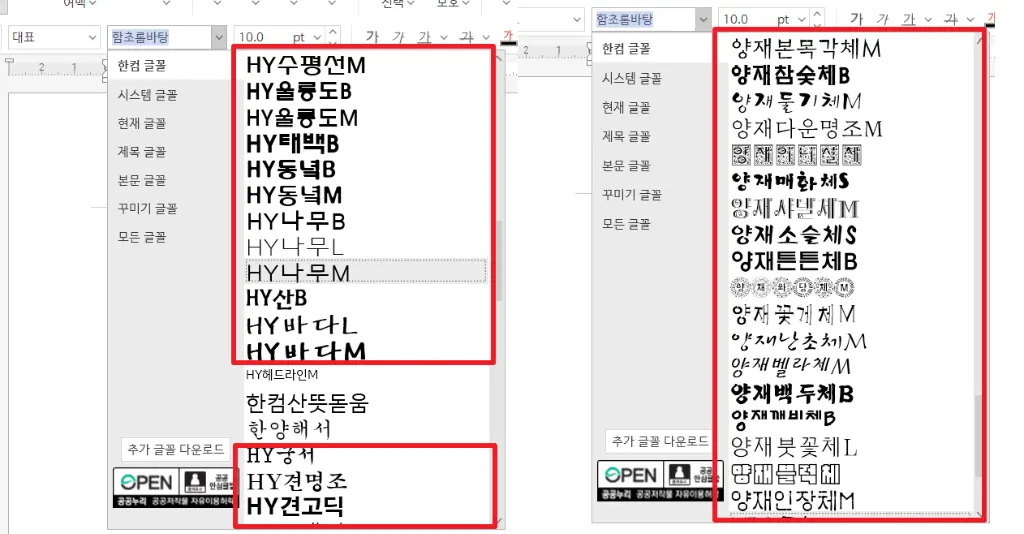
한컴 폰트(HY폰트) 관련 저작권 침해 내용증명 수령 시 당황하지 않고 대처하는 실무 전략과 상업용 무료 폰트 전환 방법을 안내합니다.
평소처럼 디자인 작업을 하거나 유튜브 자막을 달았을 뿐인데, 어느 날 갑자기 법무법인으로부터 '폰트 저작권 위반'이라는 내용증명을 받는다면 얼마나 당황스러울까요? "나는 내 컴퓨터에 원래 깔려 있던 폰트를 썼을 뿐인데?"라고 억울해하실 수 있지만, 바로 이 지점이 저작권 사냥꾼들이 노리는 가장 흔한 덫입니다.
오늘은 수많은 사람들을 공포에 떨게 하는 폰트 저작권 내용증명의 진실과, 억울한 피해를 막기 위한 완벽 대처법을 상세히 파헤쳐 보겠습니다.
1. 오해 금지: '한글 문서'를 작성한 것은 죄가 아닙니다
한컴오피스 한글 폰트 목록 예시
가장 먼저 확실히 짚고 넘어가야 할 점이 있습니다. 한글(한컴오피스) 프로그램 내에서 문서를 작성하기 위해 'HY폰트', '양재체' 등을 사용하는 것은 전혀 저작권 위반이 아닙니다. 이는 한컴오피스를 구매하거나 설치하면서 정당하게 획득한 사용 권리 범위에 포함되기 때문입니다.
한컴 공식 채널과 문화체육관광부 모두 "한컴오피스 제품 내의 기능을 이용한 결과물은 폰트파일을 활용하는 것으로 저작권 침해가 되지 않는다"고 공식 확인한 바 있습니다.
💡 핵심 요약: 문서를 작성하고 종이로 인쇄하여 배포하는 행위 자체에는 아무런 법적 문제가 없습니다. 안심하고 사용하셔도 됩니다.
2. 진짜 문제는 '다른 프로그램'에서의 무단 사용입니다
그렇다면 도대체 언제 문제가 발생하는 걸까요? 한컴오피스를 설치하면 컴퓨터 시스템(윈도우 폰트 폴더 등)에 HY폰트 파일이 자동으로 설치됩니다. 문제는 이 폰트들의 라이선스(사용 허락) 범위입니다.
이 번들 폰트들은 오직 '한컴오피스 프로그램 내에서만' 사용하도록 약관에 명시되어 있는 경우가 많습니다. 하지만 시스템 폰트 폴더에 설치되다 보니, 포토샵, 일러스트레이터, 프리미어 프로, 파워포인트 등 컴퓨터에 깔린 다른 프로그램에서도 이 폰트들이 목록에 뜨게 됩니다.
사용자가 무심코 포토샵에서 광고 이미지를 만들거나 프리미어에서 영상 자막을 넣을 때 이 폰트를 선택하게 되면, 바로 '범위를 벗어난 무단 사용'이 되어 분쟁의 씨앗이 됩니다.
⚠️ 실제 사례: 비영리단체 직원 A씨는 유튜브에 올린 영상에 HY그래픽체를 자막으로 사용했다가 법무법인으로부터 등기를 받고 77만 원 상당의 패키지 구매를 요구받았습니다. 한컴오피스 설치 시 자동으로 설치되는 폰트였지만, 영상 편집 프로그램에서 사용한 것이 문제였습니다.
3. 법원은 '폰트 프로그램'과 '결과물'을 엄격히 구분합니다
내용증명을 받았을 때 무조건 겁먹을 필요가 없는 이유는, 대법원과 행정기관의 명확한 판단 기준 때문입니다. 핵심은 폰트 "프로그램" 자체와 이를 이용해 만든 결과물(2차 저작물)을 구분하는 것입니다.
구분 내용 저작권 보호 여부
폰트 파일 (.ttf, .otf 등) 컴퓨터에서 글자를 구현하는 소프트웨어 ✅ 프로그램저작물로 보호
글자 모양 (서체 디자인) 글꼴의 미적 형태 자체 ❌ 저작권 보호 대상 아님 (대법원 판례)
이미지·PDF 결과물 폰트를 사용해 만든 JPEG, PNG, 인쇄물 ✅ 대체로 안전 (문체부 공식 입장)
📌 핵심 판례 및 유권해석
• 대법원 2001. 6. 29. 선고 99다23246 판결: 글자체(서체) 자체는 저작권법상 보호 대상이 아님을 명시
• 대법원 2001. 5. 15. 선고 98도732 판결: 동일 취지 확인
또한 문화체육관광부는 공식 보도자료를 통해 "폰트 파일을 직접 사용하지 않고 그 결과물을 이용한 것에 불과한 경우는 저작권법을 위반한 것이 아님"을 명확히 밝혔습니다.
4. 수백만 원을 요구하는 '합의금 장사'의 실체
저작권 침해를 주장하는 일부 법무법인들은 이러한 법적 모호성을 교묘히 이용해 공포감을 조성하는 내용증명을 보냅니다. 전형적인 수법은 다음과 같습니다.
• 탐지: 기업 웹사이트의 PDF, 카탈로그, 로고, 유튜브 영상 등에서 특정 서체 사용 여부를 자동 탐지
• 위협: "저작권법 위반으로 형사 고소 및 민사 소송을 제기할 수 착할 수 있다"는 내용증명 발송
• 요구: 최대 220만 원에 달하는 고가 라이선스 패키지 구매 강요
💬 문화체육관광부 공식 경고 (보도자료)
"내용증명을 공신력 있는 문서로 오인하여 자신이 저작권을 침해하였다고 생각하고 고가의 폰트 파일 패키지를 구매하거나 합의금 지급에 응하는 경우가 많다. 저작권 침해 여부를 충분히 검토하지 않고 합의에 응하지 않도록 주의가 필요하다."
5. 내용증명 폭탄, 이렇게 대처하세요!
만약 내용증명을 받았다면 당황해서 즉시 합의금을 입금하거나, 반대로 완전히 무시하는 극단적인 대응은 피해야 합니다. 내용증명에 대한 답변은 반드시 해야 합니다.
🛡️ 단계별 대응 전략
1. 외주 제작 여부 확인: 외주 업체에 맡겼다면 계약서에 따라 법적 책임은 제작사에 있습니다. 무조건 책임을 인정하지 마세요.
2. 침해 유형 분석: 단순 이미지 게시인지, 폰트 파일 자체를 웹 서버 등에 무단 배포한 것인지 파악하세요. 결과물 사용과 파일 배포는 법적으로 완전히 다릅니다.
3. 논리적인 서면 답변 작성: '폰트 프로그램을 무단 복제한 사실이 없음'을 명확히 하고, 과도한 합의 요구에는 응할 수 없다는 의사를 전달해야 합니다.
📝 답변서 핵심 문구 예시
"본인은 귀사가 저작권 침해로 주장하는 폰트 파일을 무단 복제하거나 제3자에게 배포한 사실이 없습니다. 해당 이미지는 정당하게 설치된 소프트웨어 환경 내에서 제작된 결과물로, 문화체육관광부의 공식 유권해석에 따라 저작권 침해에 해당하지 않습니다. 귀사의 과도한 합의 요구에는 응하기 어려우며, 법적 절차가 필요하다면 정식 소송을 통해 대응하겠습니다."
6. 가장 완벽한 예방책: 상업용 무료 폰트 활용
이러한 피곤한 분쟁을 원천적으로 차단하는 가장 스마트한 방법은, 처음부터 상업용 무료 폰트만 사용하는 환경을 구축하는 것입니다.
학교안심폰트 (150종) 교육저작권지원센터 개인·상업 모두 무료, 교육 현장 특화 OFL
카페24 폰트 카페24 웹폰트 지원, 고품질 상업용 무료 자체 무료 라이선스
📌 무료 폰트 다운로드 사이트 (공식)
✅ OFL (Open Font License)란?
국제 SIL이 2005년에 만든 오픈폰트 라이선스로, 개인·기업·상업적 용도 모두 자유롭게 사용할 수 있습니다. 수정과 재배포도 허용되며(단독 판매 및 라이선스 변경 제외), 폰트 분쟁에서 가장 안전한 선택지입니다.
🔍 PC 폰트 점검 방법
한국저작권보호원 '내 PC 폰트 점검' 프로그램을 통해 시스템 내 불필요한 번들 폰트를 사전에 삭제하는 것이 좋습니다.
점검 후 HY폰트, 양재체 등 한컴 번들 폰트는 삭제하거나 한컴오피스 전용 폴더로 이동하는 것을 권장합니다.
7. FAQ: 자주 묻는 질문 모음
Q. 유튜브 썸네일에 HY폰트를 썼는데 문제가 되나요?
썸네일은 이미지 결과물이므로 폰트 파일 자체를 배포한 것이 아닙니다. 문체부 유권해석상 직접 침해로 보기 어렵지만, 분쟁 소지를 완전히 없애려면 상업용 무료 폰트(나눔스퀘어, Noto Sans KR 등)로 교체하는 것이 가장 안전합니다.
Q. 블로그나 웹사이트에 HY폰트를 웹폰트로 올렸는데요?
이 경우는 폰트 파일 자체를 서버에 올려 배포하는 행위에 해당할 수 있어 위험합니다. 즉시 OFL 라이선스 폰트로 교체하시기 바랍니다.
Q. 합의금을 이미 냈는데 돌려받을 수 있나요?
합의서에 서명했다면 반환이 어렵습니다. 서명 전이라면 법무부 법률구조공단(국번 없이 132)에 무료 상담을 먼저 받으세요. 실제 침해 여부와 합의금 적정성을 전문가가 판단해 드립니다.
Q. 외주 업체에 맡긴 디자인인데 저도 책임이 있나요?
계약서에 저작권 책임 조항이 있다면 외주사에 구상권 청구가 가능합니다. 계약서를 반드시 보관하고, 내용증명 수령 즉시 외주사에 통보하세요.
Q. 내용증명을 무시하면 어떻게 되나요?
내용증명 자체는 법적 강제력이 없지만, 무시는 금물입니다. 답변 없이 방치하면 상대방이 실제 소송이나 형사 고소로 이어갈 근거를 마련해 줄 수 있습니다. 반드시 서면으로 대응 의사를 밝히세요.
폰트 저작권, 정확히 알면 충분히 방어할 수 있습니다. 오늘부터라도 작업 컴퓨터의 폰트 라이선스를 꼭 점검해 보시고, 억울한 분쟁으로부터 소중한 자산을 지키시길 바랍니다! 🛡️